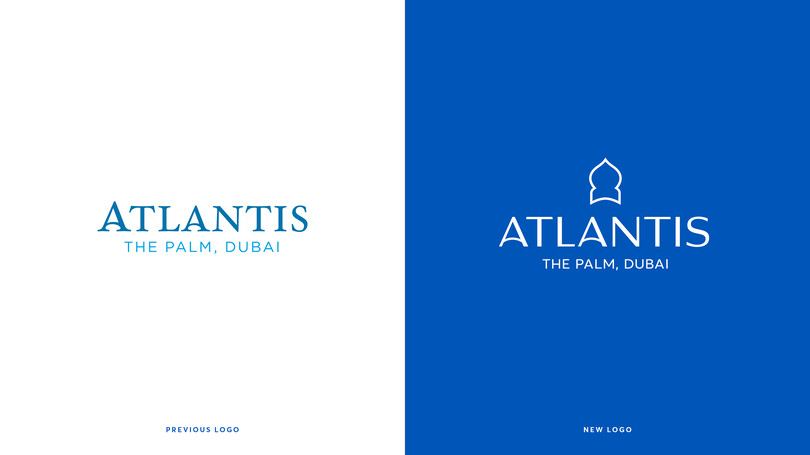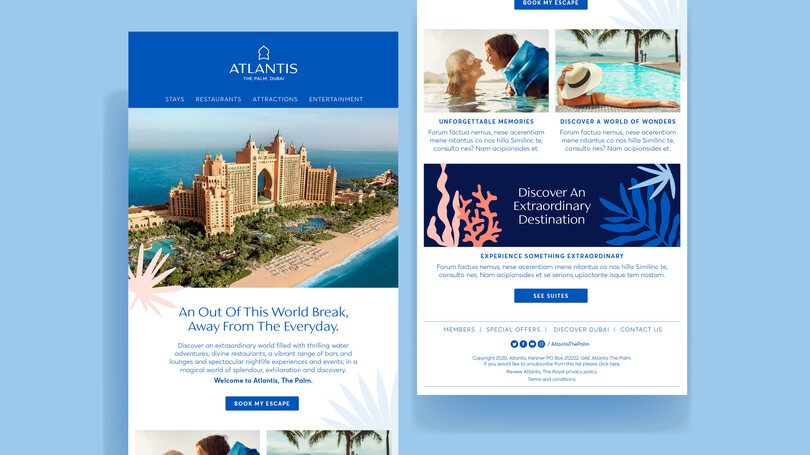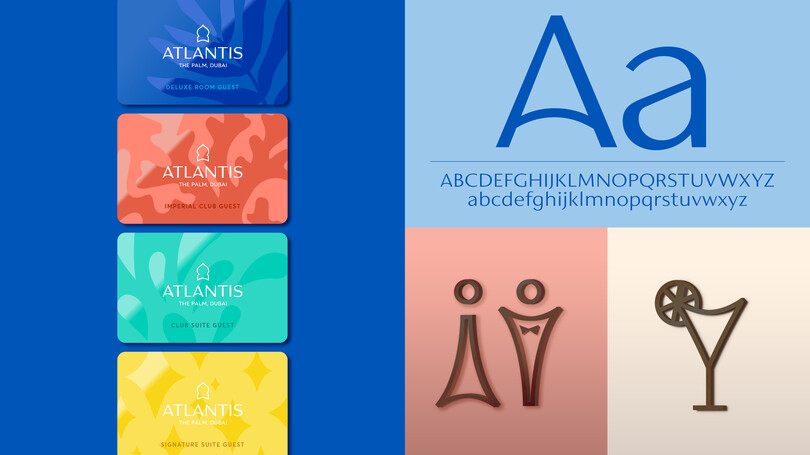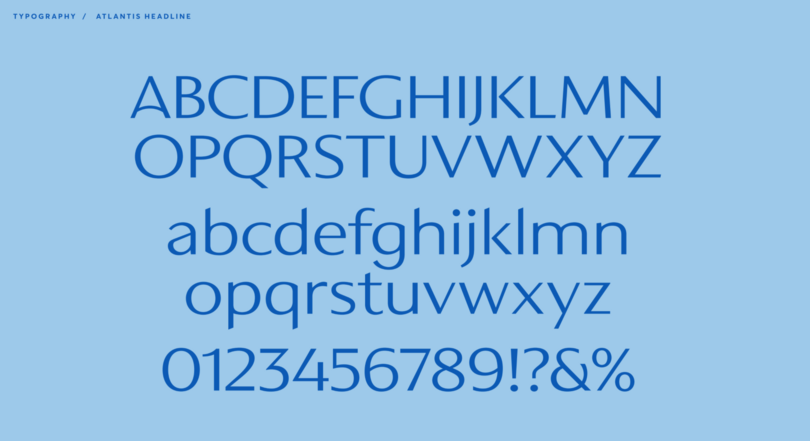
Uma nova identidade de marca para a Atlantis Resorts.
“ A fonte é cultura; as nuances das formas das letras refletem o tempo e o lugar. Para marcas globais estabelecidas, a localização e o patrimônio oferecem pistas vitais para estabelecer um tom de voz autêntico. A nova fonte Atlantis atinge esse objetivo, uma fonte distinta e elegante que transmite a sensação das experiências exclusivas e incomparáveis da Atlantis. ”
Phil Garnham, Diretor Criativo de Tipografia, Monotype.
A Futurebrand e a Kerzner International chamaram a equipe do Monotype Studio para ajudar a revitalizar a identidade da Atlantis, marca de hotéis de luxo que opera tanto o The Palm quanto o The Royal em Dubai e Sanya, na China. Esta é a primeira atualização de marca do grupo desde a inauguração do The Palm em 2008 e um movimento para unificar a identidade visual de todas as propriedades.
A Futurebrand trabalhou com a Atlantis para criar um novo logotipo para a marca, uma evolução modernizada da fonte original que manteve as traves horizontais arqueadas do “A” original, agora incorporadas em um novo estilo sem serifa com contraste. A ideia estava a caminho, mas algo ainda não estava totalmente certo.
A Futurebrand pediu ao Monotype Studio para colaborar no projeto, focando em detalhes de design e ajudando a dar vida à visão da marca por meio refinamento das letras. Exploramos o peso do logo, contraste, proporções, espaçamento e curvas de todos os caracteres para finalizar a nova marca e criar uma iteração confiante das formas das letras.
O design de logotipos é uma disciplina própria, que exige um conjunto único de habilidades e demanda uma abordagem diferente em relação ao design de uma fonte. Mas o design e a arte dos logotipos podem ser uma ótima introdução ao processo de design de fontes personalizadas. Juntos, começamos a expandir a ideia de um estilo de fonte personalizado único e que pudesse servir como um elemento de ligação entre todas as propriedades da marca. Um aspecto-chave da identidade era a sinalização da marca e o sistema de orientação do hotel. A Futurebrand havia criado um conjunto de ícones personalizado para o ‘The Royal’, e vimos uma oportunidade de criar uma fonte que fosse influenciada por isso, construindo uma linguagem visual coerente com o novo logotipo e com a iconografia.
Nosso objetivo era criar uma fonte de cabeçalho apenas em letras maiúsculas que se tornasse sinônimo da marca do hotel ‘The Royal’, refletindo as culturas do Oriente Médio, as preferências tipográficas regionais e o objetivo da Atlantis de inovar em torno do conceito de uma marca de luxo nos dias de hoje. Também precisávamos estar atentos à forma como as fontes seriam usadas na sinalização e, por sua vez, às limitações da fabricação dessas sinalizações. As formas das letras seriam cortadas em aço em uma variedade de tamanhos, por isso equilibramos os pesos e realizamos testes para evitar traços de letras que fossem muito finos. Criamos um design de fonte inspirado nos arcos suaves do logotipo e na arquitetura distintiva do The Palm, porém mais robusto para atender às necessidades funcionais da marca.
À medida que a identidade da marca crescia com o número de aplicações e casos de uso, a Futurebrand nos contatou para expandir a fonte em um conjunto completo de caracteres latinos com letras maiúsculas e minúsculas, com o objetivo de criar continuidade em toda a marca Atlantis. As formas das letras minúsculas foram fortemente influenciadas por um senso de culturas caligráficas, trazendo a natureza caligráfica da fonte árabe para o alfabeto latino.
“ Ao entrar em uma nova década, precisávamos de uma nova visão para a Atlantis, que capturasse nossa missão de ser extraordinários em tudo o que fazemos. Nossa marca é divertida, criativa e experimental, e isso realmente precisava se refletir em nossa marca registrada e identidade visual. ”
Hanan Eissa, Vice-Presidente de Marketing & RP, Atlantis